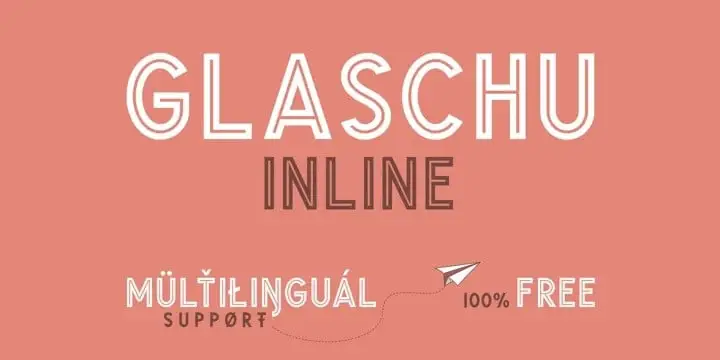
Glaschu Sans Serif Font – Download Grátis
Glaschu Sans Serif é uma escolha perfeita para projetos atuais e futuros. Criado pela Braw Type, esta fonte tipo sans serif apresenta uma aparência moderna e bold que se destaca no design gráfico. Com cinco pesos de fontes diferentes e duas opções adicionais de estilos esculpidos, ela oferece uma aparência limpa e firme que faz dela uma escolha óbvia para aplicações como headings, branding, sinalização, publicidade, layouts de revistas e muito mais. Combine os estilos esculpidos com Glaschu ExtraBold para criar efeitos ainda mais criativos em suas letras. Glasca Sans Serif é a fonte perfeita para quem busca um estilo moderno que se adapta às necessidades do seu projeto atual ou futuro.